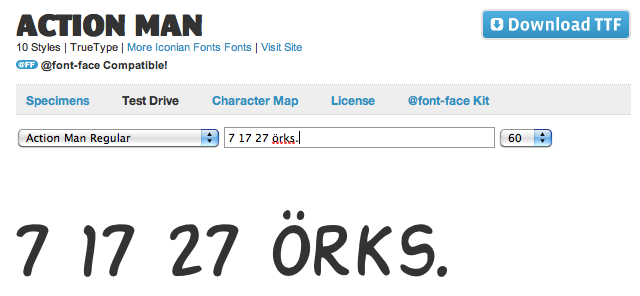
ich bin wahrlich kein großer fußballfan, schaue mir eigentlich nur WM und EM an
und ich muss gestehen ich habe noch nie ein spiel von unserer frauenmannschaft —
ist das wort überhaupt in diesem sinne richtig? — von unserer frauschaft :lol: gesehen,
darum bin ich gespannt was für einen fußball diese spielen. noch gespannt bin ich aber
wie immer auf die trikotbeschriftungen. welche trikotdesign bekommt die grafische
rote karte, welcher name ist am meisten gesperrt und welche ideenlosigkeit wurde
diesmal bei den ziffern verwendet. ich freu mich auf eure beispiele und behaupte mal,
im bereich trikot haben die deutschen frauen schonmal verloren.
Ui, die Beschriftung ist ja mal fies. :mad:
Außerdem hab' ich Angst vor Frauen, die scheinbar stärkere Oberschenkel als ich, mit meinen 130kg Kampfgewicht, haben.
... oder bin ich aus meiner Schulzeit traumatisiert, als bei den (seltenen) Fußballspielen Mädchen gegen Jungen die Devise der Mädchen noch "Wenn wir schon nicht den Ball treffen, treten wir ihnen wenigstens die Schienbeine zu Klump" lautete?
Das ist doch eh kein richtiger Fußball, da brauchen die auch keine vernünftigen Trikots und da reicht doch die Comic Sans. <ironieoff>
Das schienen mir die Trikots auszudrücken :-o
Traurig aber wahr. :neenee: Dabei gibt es doch so viel Fashion-Designer, die sich freuen würden wie ein Schnitzel, wenn sie schicke Trikots gestalten dürften … :-?
Scheußliche Trikots ... da bleibt nur eines: Ausziehen und ohne Fußball spielen. Man kann die Nummern ja mit Fingerfarben aufmalen. ;-)
Im Umkehrschluss würde ich mich aber nicht freuen wie ein Fashion-Designer, wenn ich so was gestalten ›dürfte‹ ... :neenee:
Obwohl, mal eine Schrift für Trikots entwerfen, könnte interessant sein: besser als dieses Vorbild wird’s auf jeden Fall und Haue aus der Fachriege ist auch garantiert, egal wie viel Mühe man sich gibt 8-)
Scheußliche Trikots ... da bleibt nur eines: Ausziehen und ohne Fußball spielen. Man kann die Nummern ja mit Fingerfarben aufmalen. ;-)
Ich nehme alles zurück, für den Job bin ich zu haben!!!
Bodylettering :-P
Scheußliche Trikots ... da bleibt nur eines: Ausziehen und ohne Fußball spielen. Man kann die Nummern ja mit Fingerfarben aufmalen. ;-)
Chauvinist!
Ich nehme alles zurück, für den Job bin ich zu haben!!!
Bodylettering :-P
:grusel: Die würd ich nicht mal mit Deinen Fingern anmalen ... :shock:
Find die Lettern verspielt, bodenständig, simpel und belastbar. Vetragen Falten, Schweiß und auch mal Schmutz. Nichts für Intellektuelle oder solche die sich dafür halten.
Paßen gut zu Menschen, die sich selber nicht gar so wichtig nehmen.
Paßen gut zu Sportlern, denen es piepegal ist, was auf dem Trikot hinten draufsteht.
Paßen gut zu der erfrischenden Unbekümmertheit der deutschen Fußballmädels.
Im Schweiße meines Angesichts habe ich für RoMi Fußballtrikots gesucht – um meinen On-Topic-Score mal wieder ein bisschen zu verbessern. ;-)
Peinlich, das deutsche Hemd ist wirklich eines der schlechtesten. Gut gefallen mir die Engländer und Schweden, jedenfalls von vorne.
Scheußliche Trikots ... da bleibt nur eines: Ausziehen und ohne Fußball spielen. Man kann die Nummern ja mit Fingerfarben aufmalen. ;-)
:roll:
Wozu ausziehen? Wie man nur unschwer an den Trikots erkennen kann geht das doch auch angezogen? Als echte Alternative wären da vielleicht Schabloneschriften möglich. Glaser Stencil oder Stencil BT wären aber für deutsche Qualitätsprodukte unangemessen. Eine DIN-Schablonierschrift sollte es schon sein!
Also zusammenfassend kann man doch eigentlich sagen, dass Trikots generell fies aussehen, oder? Speziell mit dem ganzen Sponsorenklimbim drauf. Dem Fass den Boden ausschlagen tun in meinen Augen aber die Designer des nordkoreanischen Teams – die haben offensichtlich auch noch hängende Schultern in die Shirts eingebaut … ;-)
Knapp daneben kann auch mal weit vorbei sein.